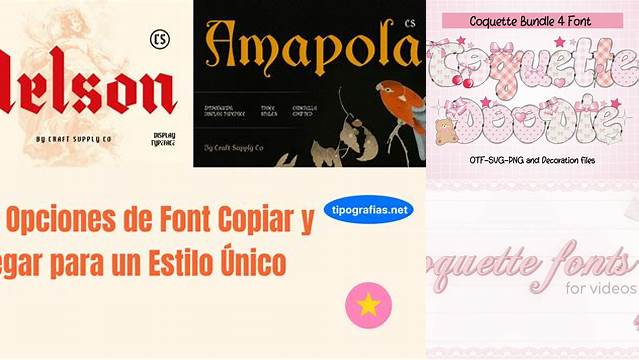
Fonts Coquette: Copiar Y Pegar Textos Adorables
¡Hola, chicos! ¿Alguna vez se han topado con esos textos súper coquetos y adorables que parecen sacados de un cuento de hadas? Esos textos con letras cursivas, florituras y un toque mágico que los hace irresistibles. Pues bien, hoy vamos a sumergirnos en el mundo de las fonts coquette copiar y pegar, y les prometo que al final de este artículo serán unos verdaderos expertos en el tema.
¿Qué son las Fonts Coquette y por qué son tan Populares?
Fonts coquette son mucho más que simples letras; son una declaración de estilo. Se caracterizan por su elegancia, feminidad y ese toque vintage que las hace tan especiales. Piensen en las letras de los cuentos antiguos, en la caligrafía de las invitaciones de boda, o en esos letreros de tiendas chic que tanto nos gustan. Las fonts coquette evocan una sensación de nostalgia, romanticismo y sofisticación que las convierte en la opción perfecta para darle un toque especial a nuestros proyectos.
La Magia de la Estética Coquette
La estética coquette, de la cual las fonts son una parte fundamental, se ha convertido en una tendencia arrolladora en redes sociales como TikTok e Instagram. Esta estética celebra la feminidad en todas sus formas, desde los colores pastel y los encajes hasta los lazos y las perlas. Las fonts coquette encajan a la perfección en este universo estético, aportando ese toque final de encanto y delicadeza. Si quieren que sus publicaciones, invitaciones o diseños tengan ese je ne sais quoi que los hace irresistibles, las fonts coquette son su mejor aliado.
¿Dónde Podemos Usar las Fonts Coquette?
Las posibilidades son infinitas, ¡chicos! Aquí les dejo algunas ideas para que empiecen a experimentar:
- Redes Sociales: Denle un toque único a sus publicaciones de Instagram, TikTok o Facebook. Usen fonts coquette en sus historias, biografías o pies de foto para destacar y atraer miradas.
- Invitaciones y Tarjetas: ¿Están organizando una fiesta, una boda o un baby shower? Una font coquette en la invitación marcará la diferencia y hará que sus invitados se sientan especiales desde el primer momento.
- Diseños Gráficos: Si son diseñadores gráficos, las fonts coquette pueden ser un recurso invaluable para crear logotipos, carteles, folletos y otros materiales promocionales con un estilo único.
- Proyectos Personales: ¿Quieren darle un toque especial a su diario, a sus cartas o a sus regalos? Una font coquette es la opción perfecta para expresar su creatividad y personalidad.
¿Cómo Copiar y Pegar Fonts Coquette? La Guía Paso a Paso
Ahora viene la parte divertida: ¡aprender a usar estas fonts mágicas! No se preocupen, no necesitan ser diseñadores gráficos ni tener conocimientos técnicos avanzados. Copiar y pegar fonts coquette es más fácil de lo que imaginan. Aquí les dejo una guía paso a paso para que se conviertan en unos expertos:
Paso 3: Elegir la Font Coquette Ideal
Aquí viene la parte emocionante: ¡explorar las diferentes fonts coquette que les ofrece el generador! Verán opciones con letras cursivas, con florituras, con corazones, con estrellas… ¡un verdadero paraíso para los amantes de la estética coquette! Prueben diferentes fonts hasta encontrar la que mejor se adapte a su estilo y a su proyecto.
Paso 4: Copiar y Pegar la Font Elegida
Una vez que hayan encontrado la font coquette perfecta, simplemente tienen que copiar el texto generado. La mayoría de los generadores tienen un botón de "Copiar" para facilitarles la tarea. Luego, peguen el texto donde quieran usarlo: en sus redes sociales, en sus invitaciones, en sus diseños… ¡donde sea que quieran agregar un toque de magia!
Paso 5: ¡Disfrutar del Resultado!
¡Listo! Ya tienen su texto transformado con una font coquette encantadora. Ahora, admiren el resultado y disfruten de cómo su creación se destaca del resto. Verán cómo una simple font puede hacer una gran diferencia y cómo sus proyectos cobran vida con un toque de elegancia y feminidad.
Consejos y Trucos para Usar Fonts Coquette como un Profesional
Ahora que ya saben cómo copiar y pegar fonts coquette, quiero compartir con ustedes algunos consejos y trucos para que las usen como unos verdaderos profesionales:
Combinen Fonts con Inteligencia
¡A Crear Magia con las Fonts Coquette!
Espero que esta guía les haya sido útil, chicos. Ahora tienen todas las herramientas que necesitan para sumergirse en el mundo de las fonts coquette copiar y pegar y crear diseños encantadores. Recuerden que la clave está en experimentar, divertirse y dejar volar su imaginación. ¡Así que manos a la obra y a crear magia con las fonts coquette!